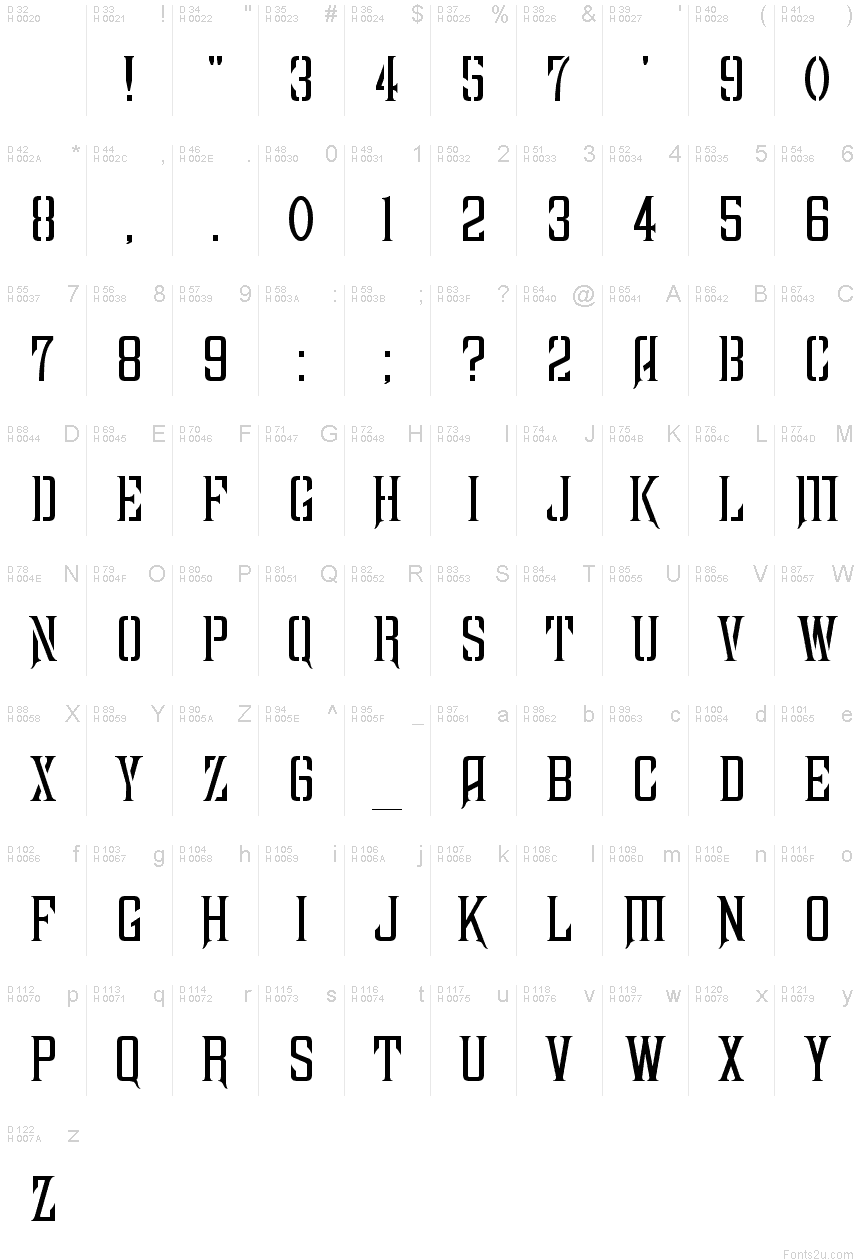
Farquharson autorstwa Davida Vereschagina to darmowy krój gotycki o ostrym, runicznym charakterze. Wysokie, wąskie znaki przypominają kamienne filary, a zahaczone krzywizny i klinowe cięcia nadają tekstowi archaiczny, „wykuty” wygląd. Font sprawia wrażenie wyjętego z dawnych pieczęci lub zniszczonych sztandarów, a mimo to światło między literami jest na tyle wyważone, że zapewnia czytelność na pierwszy rzut oka.
Farquharson pozwala nadać dramatycznego wyrazu okładkom książek fantasy, logotypom zespołów metalowych, tytułom gier RPG, średniowiecznym plakatom, projektom tatuaży czy nastrojowym ulotkom. Ten darmowy krój najlepiej prezentuje się w dużym rozmiarze i z odpowiednim oddechem, a w składzie tekstu dobrze komponuje się z czystymi, geometrycznymi krojami bezszeryfowymi, które nie przytłaczają jego mrocznej, rytualnej energii.
A Rune font, created by David Vereschagin. Copyright 1991.